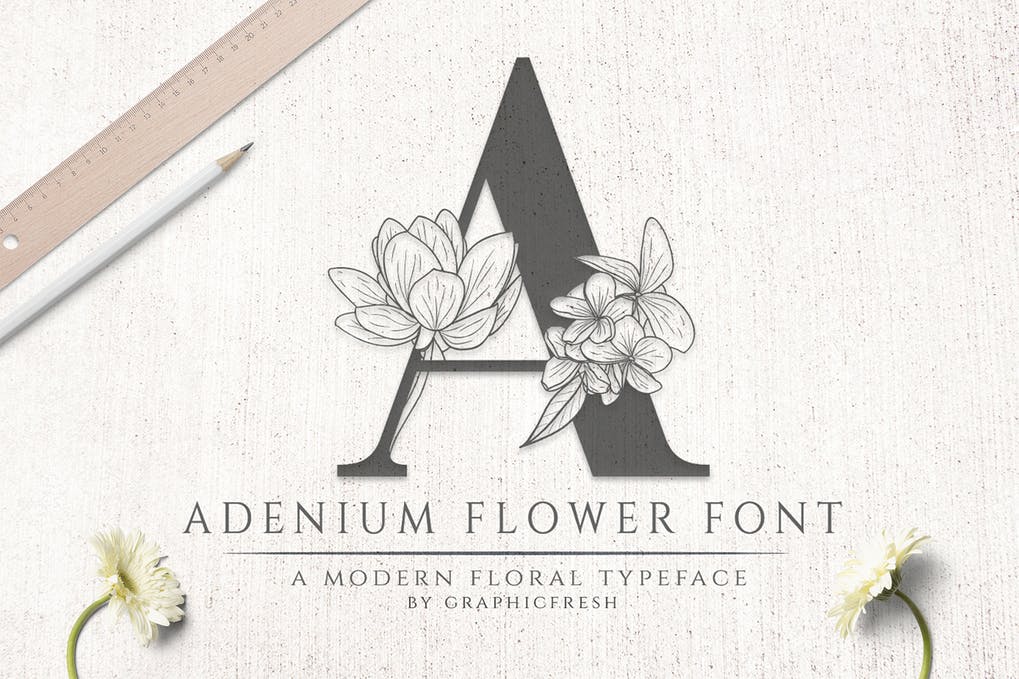
Adenium Flower Font
Diese Schriftart ist von Frangipani-Blumen inspiriert. Im Lateinischen heißt es "Adenium". Eine Blume, die beim Betrachten sehr schön ist. Also wende ich es auf eine Schriftart an. Der Serifenstil ist perfekt für diese Blume. Es ist ideal für Hochzeiten im Dschungel, Meer und Kreuzfahrt, für Branding und Logos - Restaurant, Hotels, Strandresort und vieles mehr. Diese Schriftart hilft, eine einzigartige Marke, ein stilvolles Logo, eine anmutige Hochzeitseinladung zum Ereignis oder eine konzeptionelle Visitenkarte in den Minuten zu entwerfen.
Diese Schriftart besteht aus zwei Versionen jedes Zeichens mit Ausnahme von Zahlen und Zeichen. Sie finden verschiedene Versionen zwischen Groß- und Kleinbuchstaben. Wenn Sie diese Schriftart verwenden, werden Sie eine enorme Sensation in Ihrem Design spüren.